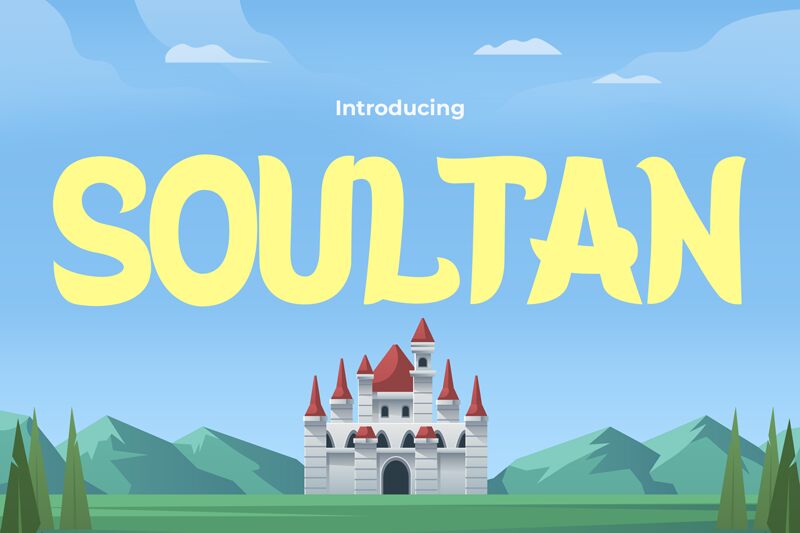
Soultan od Pinisiart to darmowy, szeryfowy font typu display w stylu retro, inspirowany estetyką plakatów z lat 70. Litery są masywne i pełne dynamiki, z zaokrąglonymi bokami, zwężeniami w łączeniach i szerokimi, rozkloszowanymi zakończeniami. Nadaje to wielkim literom falisty, niemal płynny rytm, przy zachowaniu ich dostojnego charakteru.
Krój ten świetnie sprawdzi się na okładkach albumów, w identyfikacji wizualnej kawiarni, na okładkach książek, w nagłówkach redakcyjnych czy na opakowaniach, wszędzie tam, gdzie potrzebny jest ciepły, vintage'owy klimat. Dzięki swoim przerysowanym krzywiznom i wyrazistym stopkom, SOULTAN świetnie wygląda również w tytułach, na plakatach czy w monogramach, nadając nawet krótkim słowom mnóstwo charakteru.